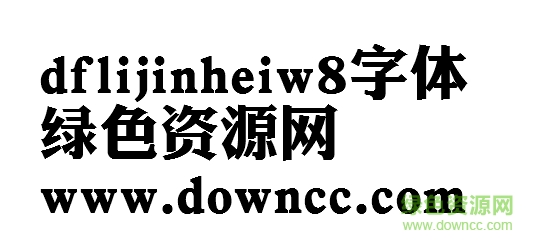
dflijinheiw8 regular简体
dflijinheiw8是什么字体
dflijinheiw8 regular是华康俪金黑W8的早期版本,当时字体库还不够全面,部分繁体体无法正常显示,绿色资源网小编推荐大家使用华康俪金黑W8字体,更好的运用于艺术设计、海报设计、排版印刷等诸多领域!
dflijinheiw8字体特色
dflijinheiw8是一款线条粗黑、字体方正的华康字体,该字体适用于图片logo、广告设计、印刷包装等应用!